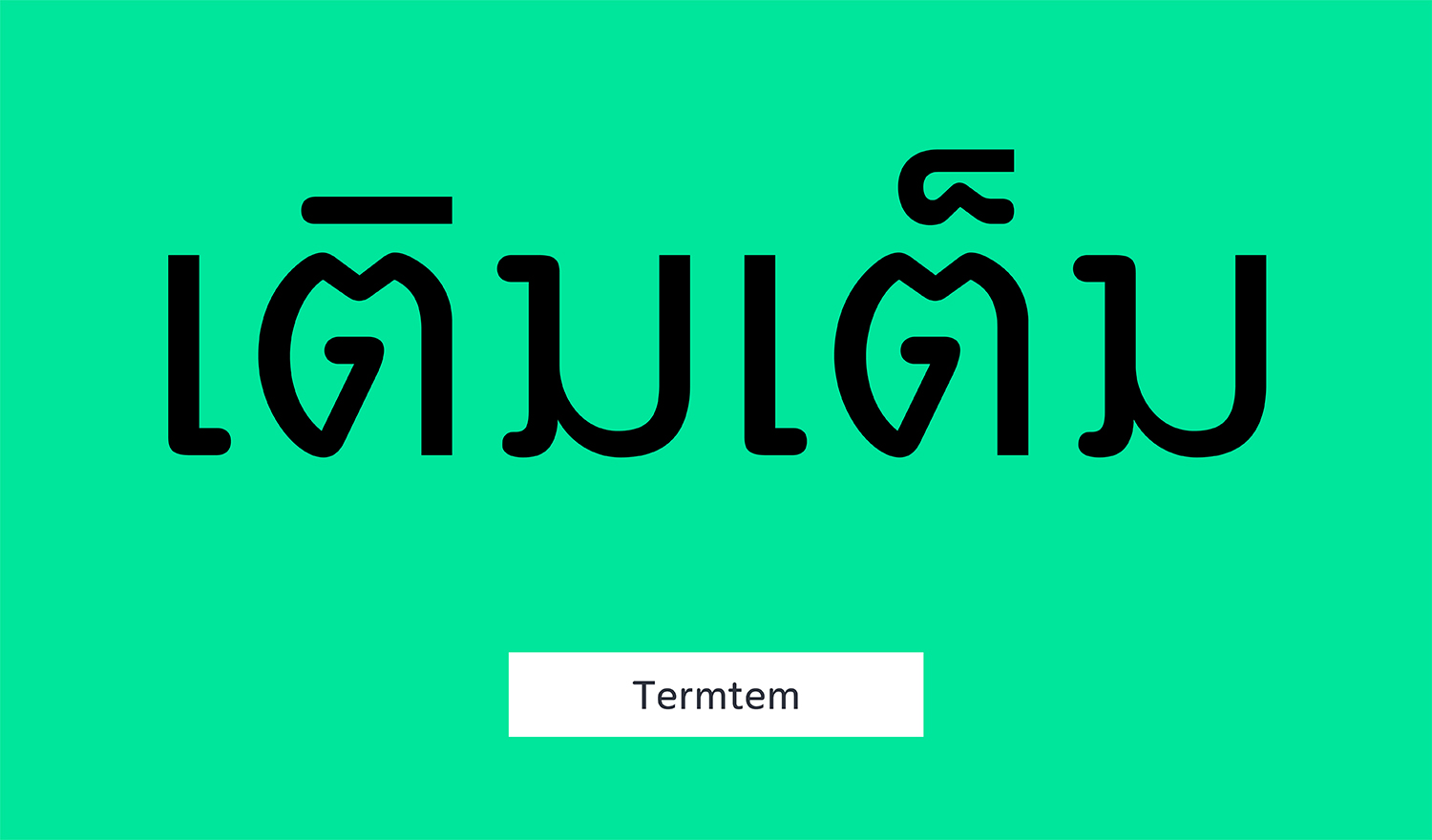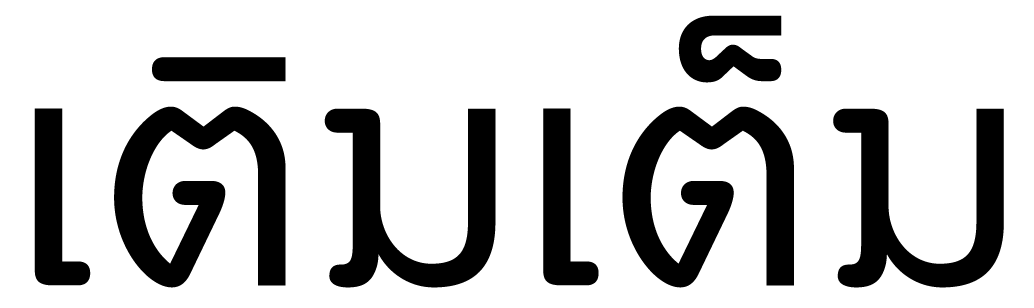
- 텀템은 둥글거나 각진 획맺음 표현이 혼합되어 있으며, 태국 문자 획 끝의 둥근요소인 '루프'가 생략된 현대적인 스타일의 폰트입니다.
이는 가볍고 편안하면서도 즐거운 분위기를 만들어내기 때문에, 마케팅 커뮤니케이션을 위한 좋은 선택이 될 것입니다.
폰트 정보 구분 디자인 폰트디자인 Anuthin Wongsunkakon, Sasikarn Vongin, Supakit chalermlarp 디자인디렉팅 Anuthin Wongsunkakon 글자구성 Latin 1